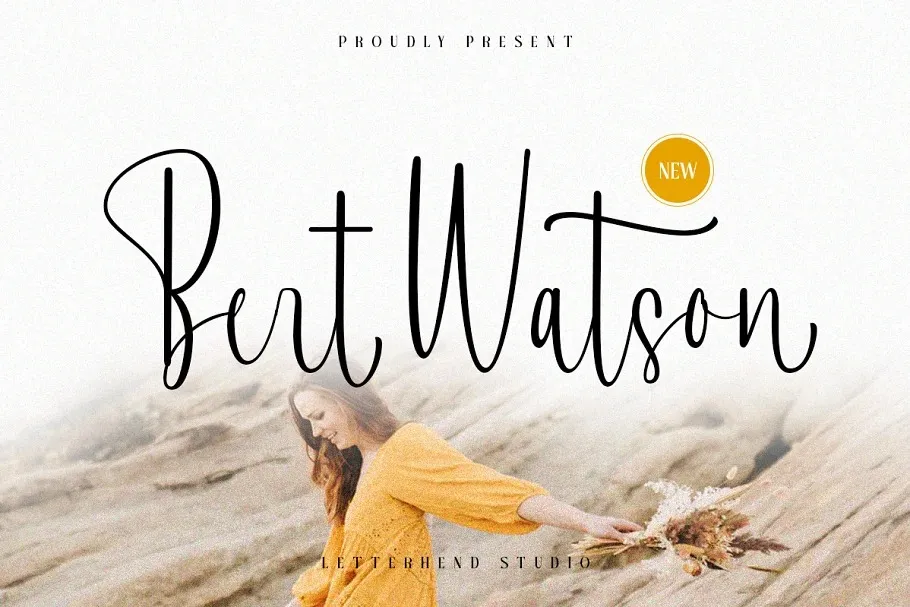
A ‘Bert Watson Font’ é uma elegante e moderna fonte de script criada pelo Studio Letterhend com uma forma autêntica deslizante. Esta fonte de script permite que você crie tipos de tipografia delicados, perfeitos para o uso em logotipos e formas formais variadas como convites, rótulos, logos, revistas, livros, cartões de agradecimento ou casamentos, embalagens, moda, maquiagem, papelaria, romances, rótulos ou qualquer tipo de propósitos publicitários. Com muitos alternativos e ligaturas contendo muitas swashes para jogar com elas, é perfeitamente adaptada a criar texturas elegantes e sofisticadas que se destacam em qualquer aplicação visual.